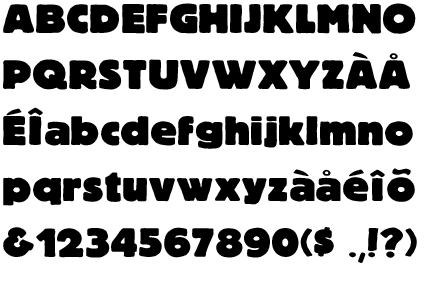
Fette Displayschrift. Name?
einer meiner neuen Kunden benutzt in seinem Signet eine Schrift, deren Namen ich nicht finden kann. Der Kunde hat keine Erkenntnis, sein Signet vor über 10 Jahren erstellt - der Kollege ist nicht mehr bekannt.
Schrifterkennung bei MyFonts hat kein direktes Ergebnis geliefert, nur ein Derivat.
das Derivat ist 100 Jahre alt! Hier aus den von Dir angegebenen Link mal zitiert:
Designers: Sidney Clyde Gaunt
Design date: 1916
Publisher: HiH
Original foundry: Barnhart Brothers & Spindler
Es gibt eine ähnliche Schriften, welche aber auch angefressen sind. Möglicherweise hat Dein unbekannter Kollege diese als Vorlage benutzt und den Schriftzug handgeblasen und mundgemalt?
Informal Black:
Publisher: Monotype Imaging
Mein Tipp: Wahrscheinlich handgemalt nach der Vorlage Informal Black. Möglicherweise existiert sogar eine fertige Schrift, welche dann aber IMHO das Derivat darstellt.